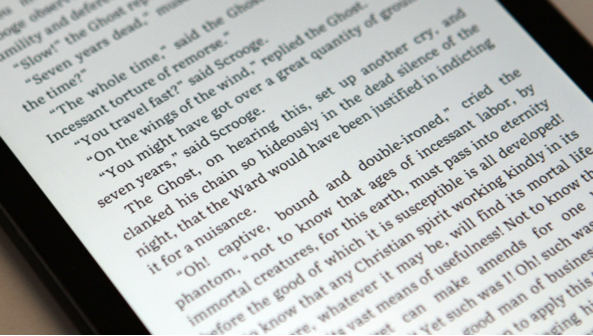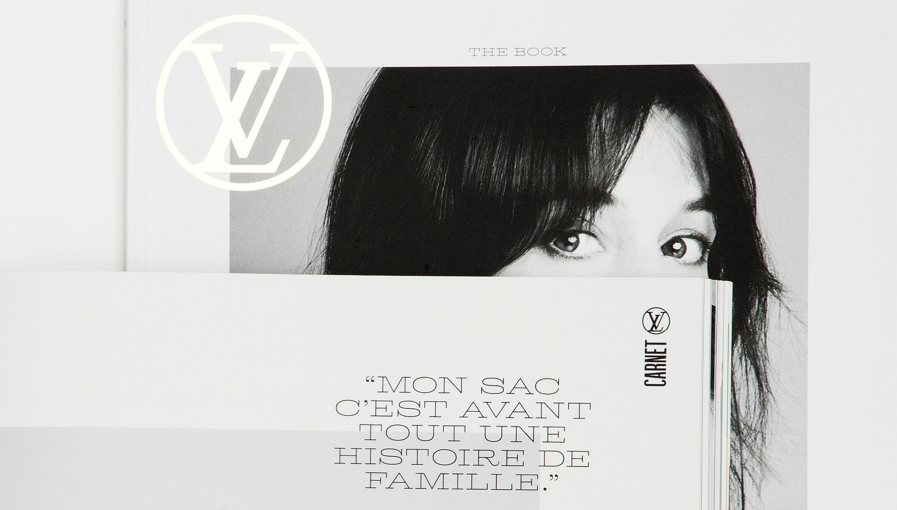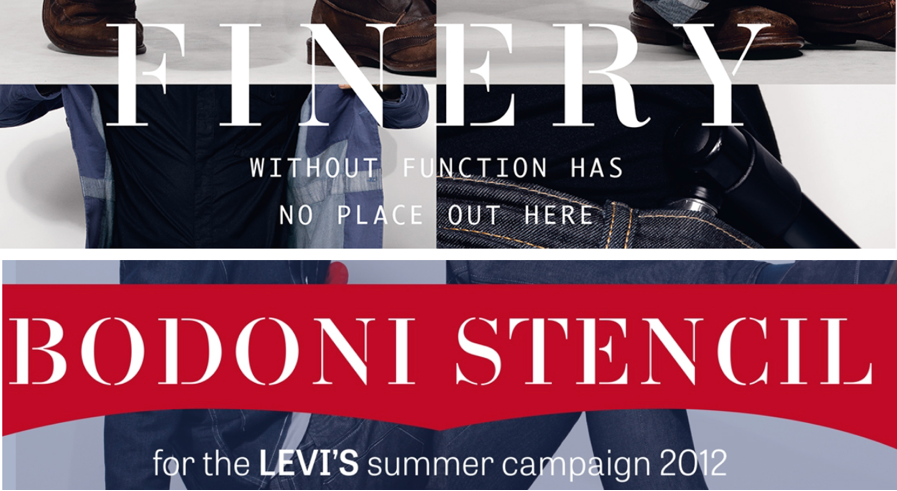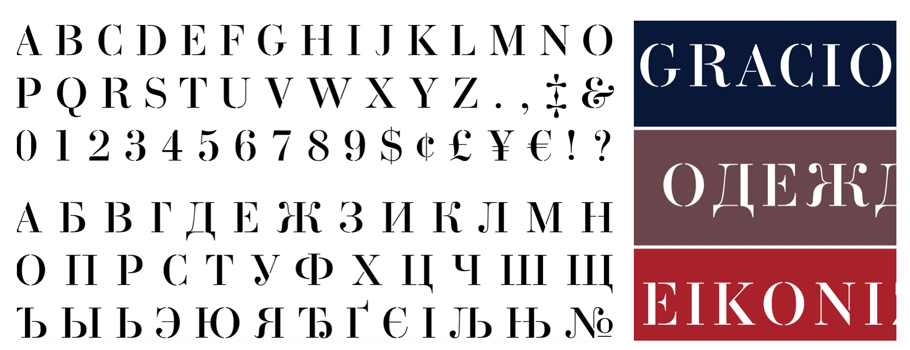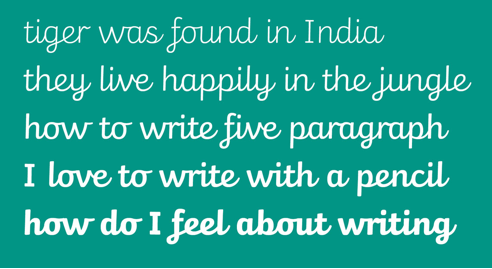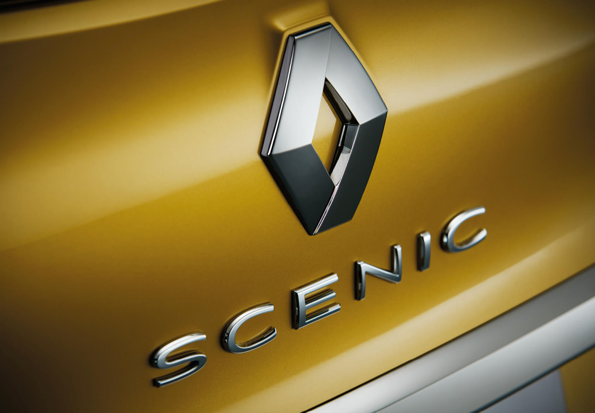
Typetogether 公司由Veronika Burian 和José Scaglione 共同成立,致力于推出高品质的字体,并通过合作的方式开发新字体项目。因此,取Type(字体)和Together(共同),组合作为公司名字。
TypeTogether 主要关注如何为专业的文本字体市场寻求创新、时尚的设计方案,并将重点放在编辑文本所用的字体上。设计在连续阅读中表现良好的字体,同时又独具风格,并拥有卓越的技术性能。TypeTogether 的产品和工作质量已经在不少国际比赛中获得认可,其中包括众多“字体指导俱乐部”(TDC)和“欧洲设计”(ED)的奖项。
Production Type是一家数字字体设计机构,总部位于巴黎。其业务范围包括零售类型在线销售,以及为工业,奢侈品和媒体行业定制字体。
由Production Type设计的Cardinal字体家族,是由字库中孕育出的第一套字体家族。它是Production Type在为Trax杂志改头换面时开发的一款核心字体。经过两年的不断完善,并经由少数几个设计工作室的实践使用,Cardinal字体家族最终投入市场,成为更多品牌与设计行业的选择。
蒙纳公司(Monotype),总部位于美国马萨诸塞州的 Woburn,是全球领先的提供字体设计、字体技术支持与相关咨询服务的供应商,拥有超过1万种字体的字体库以及世界最出色的设计师,为全球客户提供面向各种设备与应用的多语言字体解决方案。蒙纳公司的字体库是若干当今世界最流行字体(如 Helvetica®等)的发源地,也是字体设计新潮流的发布中心。
Fontworks是位于日本的字体公司。自 2017 年起,成为 Softbank Technology Corp. 集团的下属公司。以全年固定费用可自由使用 Fontworks 字体的授权产品“LETS”为代表,开展价格合理的字体服务 “mojimo”,深受纸媒和游戏、动漫等屏幕媒体的喜爱。
代表产品有“筑紫书体”系列,在硬件设备显示领域,除全年固定费用制的服务以外,还开发以通用设计为基础、追求易读性的“UD Type”,成功实现最多轻量化至 1/2 ~ 1/4 的字体“Type-S”“Type-XS”,以与九州大学的共同研究为基础,开发用于画面极小设备的字体“Type-D”等,随着时代和技术的变化而进步,提供解决方案。
Cadson Demak 建立于视觉传达刚刚开始在泰国工商各界得到认可和追捧的时候,为了帮助弥合国内原生设计人才与国际技术水平之间的鸿沟,Pongthorn Hiranpruek、Burin Hemtha和Anuthin Wongsunkakon 于2002年成立了该公司。尽管Cadson Demak 这个名字听起来很“欧洲”,但实际上它是泰语单词的抄写,意为“精选”。
Cadson Demak 早期主要服务于出版物和平面设计,2008年以后,成功发展为字体设计相关领域的专门机构,该公司以其为电信业、食品和零售业等企业提供定制字体服务而闻名,同样,它还占领了泰国本地字体零售市场额主要份额,无论是杂志、热门网站、商店招牌、食品包装,还是移动设备等,都能看到它们的字体。近年来,Cadson Demak 积极拓展国际业务,致力于加强泰国排版、平面设计活动与国际社会字体、平面设计的联系,以满足全球文化交流的需要。
Black[Foundry]是一家字体设计公司,致力于字体的创造、精炼和制造。公司成立于2014年,创始人为法国企业家、字体设计师格雷戈里·文森斯(Gregori Vincens),以及在伦敦长大的字体设计师、字体工程师杰里米·霍纳斯(Jeremie Hornus)。如今,Black[Foundry]是一个由12名人才组成的国际化团队,包括字体设计师、字体开发人员、美术总监、软件工程师、程序员和项目经理,他们都在巴黎市中心工作,并与世界各地有联系。他们擅长将设计与技术相结合,创造出具有表现力的字体。